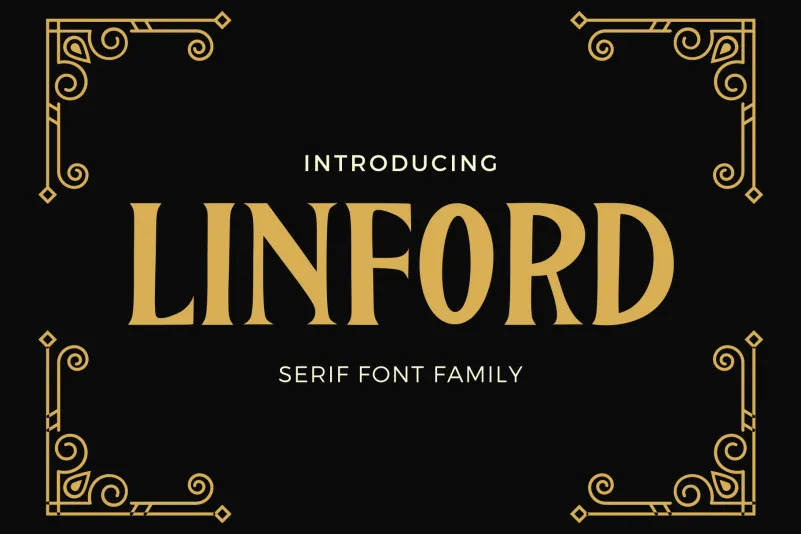
Esta é uma fonte serif que oferece profissionalismo e elegância. Ela é perfeitamente adaptada para qualquer tipo de trabalho onde a atenção ao detalhe é importante, seja para projetos de branding, banners ou postagens nas redes sociais. Yoga Letter apresenta uma fonte com 8 ligaturas elegantemente atrativas, destinadas a dar um toque especial aos seus trabalhos. Suas aplicações variam desde promoção de marcas e hotéis até invitações e produtos, permitindo-lhe expressar sua marca de maneira única e profissional em todos os tipos de mídia onde desejar. Com Linford Font, você pode garantir que seu trabalho tenha um aspecto impecável e atento ao detalhes.